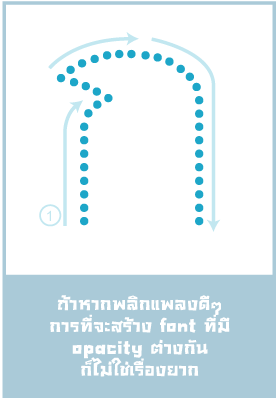
Layiji ท่าไม้ตาย ๒
ไม่มีอะไรมากหรอกครับแค่ทำ font อีกชุดเป็นชุดถมสี มันจะทำให้เล่นอะไรได้อีกเยอะเลย แต่ต้องใช้ทุกอย่างจาก font ชุดแรกนะ ห้ามเปลี่ยนอะไรทั้งนั้นน่ะครับ
วิธีใช้ง่ายๆ โดยไม่ต้องลากมาวางให้เสมอกันคือ copy ขึ้นมาอีก  layer (ถ้าเป็น illus ก็ paste in place) แล้วเปลี่ยน font เอา
ในเมื่อ user ต้องถมสีเอง ผมเลยใช้วิธีทำ font ที่ถมให้เสร็จ น่าจะใช้ง่ายกว่าน่ะครับ ผลักภาระให้ user แต่พองาม  :02:
เป็นฟอนต์เงาได้เลยนะเนี่ยเฮีย  :18:
ครีเอทมั่กมั่ก  :25:
โอ้วว
เจ๋งแฮะ
เดี๋ยวทำบ้างดีกั่ว
อันนี้เป็นตัวจุดประกายแนวคิดนี้เลยนะครับเนี่ย
เมืองโอภา(opacity)คืออะไรครับ
ปรับๆฟอนต์เงาบางตัวให้อ่านออก
ก็ปล่อยได้อีกฟอนต์เลยนะคะ สวยด้วย  :42:
เมืองโอภา(opacity)คืออะไรครับ
(ภาษาฝรั่งเขาว่า Optical Thickness จะแปลเป็นไทยว่าอะไรดี)
Opacity ความทึบโปร่ง คล้ายๆ Transperancy ล่ะมั้ง
ใน photoshop ไง opacity ความโปร่งแสงทีบแสง
ขอบคุณครับ เมืองโอภาเป็นเมืองล่องหนตามตำนานแฟนต์ดอตคอมครับ